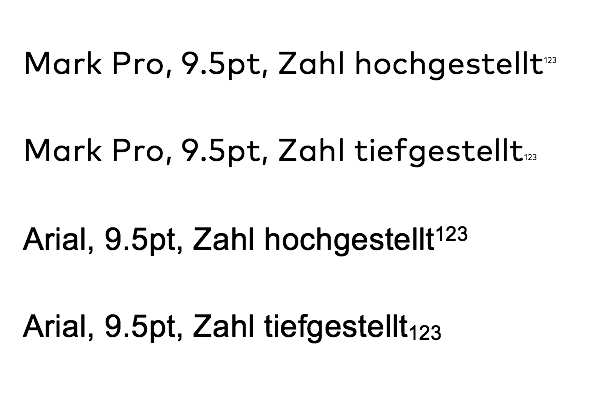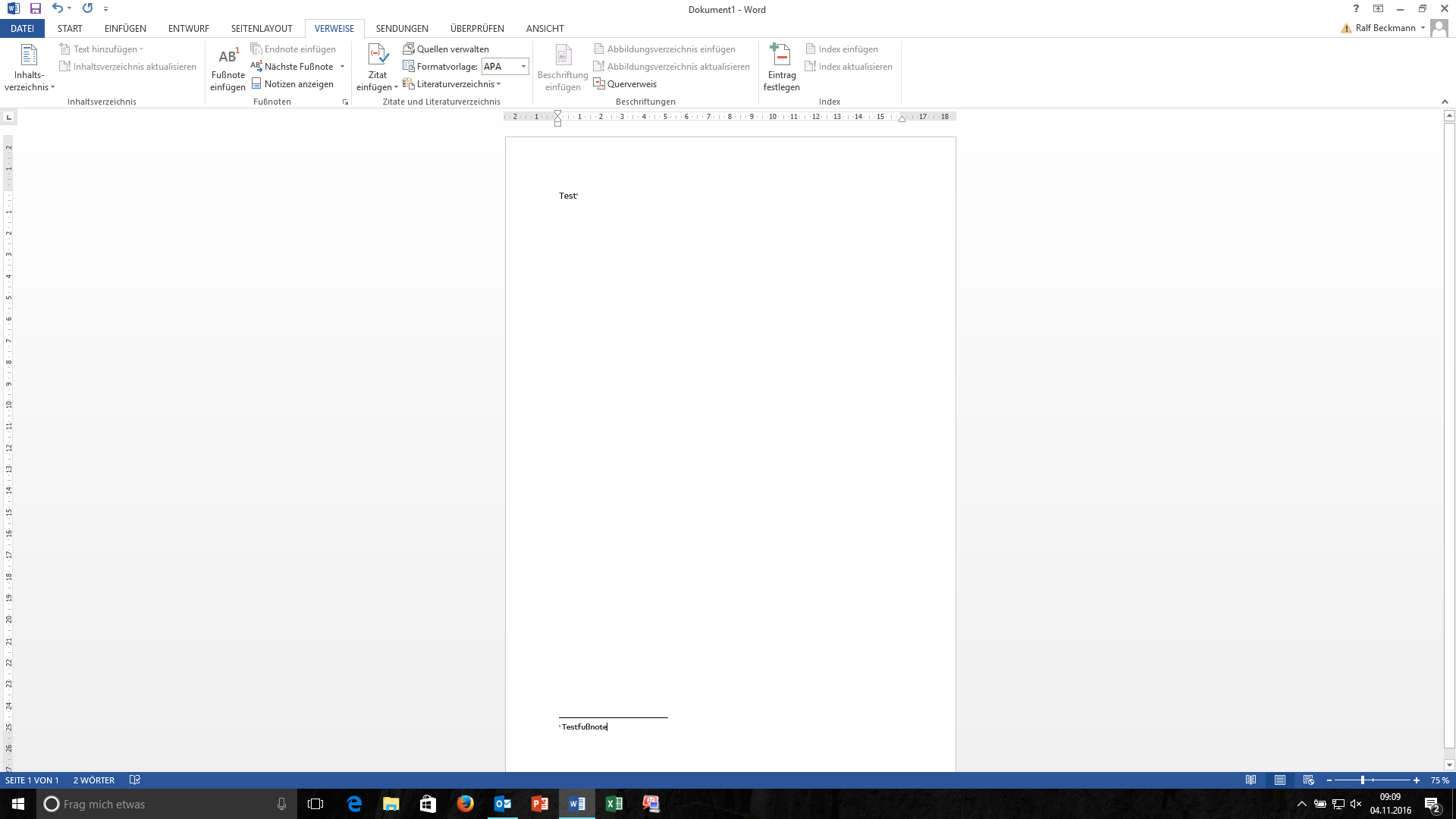
Word und FF Mark: Probleme mit Hoch-/Tiefstellen
folgendes Problem: Unser Kunde kommt mit der Schrift FF Mark (Open Type) in MS Word nicht zurecht. Hoch- oder tiefgestellte Zeichen werden viel zu klein dargestellt, siehe Screenshots. Die Option, die Schriftgröße manuell einzustellen, ist sehr umständlich und kein zufrieden stellender Weg, daher meine Frage, ob es hier bessere, konkrete Ideen zur Ursache sowie zur Lösung des Problems gibt.
Woher bekommt Word die Informationen für das Hoch-/Tiefstellen? Und lassen sich diese einstellen?
Tja, Word ist halt nix für anspruchsvolle Typografie. Prinzipiell gibt es zwei Wege, Texte mit hoch- und tiefgestellten Ziffern zu erzeugen. Der beste Weg ist es, spezielle Hoch- bzw. Tiefziffern aus modernen Fonts zu verwenden, die in Größe, Position und Strichstärke genau auf ihre Schrift abgestimmt sind.
Solche Fonts gibt es aber noch nicht so lange. Daher haben Programme wir Word diese Ziffern oft künstlich erzeugt, indem sie die normalen Ziffern verkleinerten und nach oben bzw. unten schoben. Durch das Verschieben ist die Position der Ziffern dann von Programm zu Programm verschieden und sieht mal besser und mal schlechter aus. Ein gravierenderes und praktisch unvermeidbares Problem dieser Methode ist, dass die verkleinerten Ziffern dann eine viel zu geringe Strichstärke haben. Das siehst du oben in beiden Beispielen.
Warum es aber in der Mark noch viel extremer passiert als in der Arial, hmm, da muss ich spekulieren. Vielleicht werden ja die schon angepassten Hoch- und Tiefziffern der Mark verwendet, aber fälschlicherweise noch zusätzlich verkleinert, als wenn sie normal große Ziffern wären?
Welche Word-Version wird denn verwendet? Die neuste? Die Unicode- und Opentypeunterstützung ist in den letzten Versionen besser geworden, auch wenn sie noch lange nicht als professionelle DTP-Software heran reicht.
Nun, Word trau ich nach meinen Experimenten nicht für 5 Cent in Sachen OpenType, wenns dann keine eigenen Microsoft-Schriften sind, und da hat sich bei meinen Experimenten herausgestellt, das hier Word die OpenType-Funktion intern nachbildet.
Daher schätze ich mal, das Word hier generell die Subscript und Superscript aus der normalen Schrift durch skalieren und verschieben macht.
Und da sind in der Schrift eben auch die Positions- und Skalierungswerte hinterlegt, in Fontlab bei Arial schaut das so aus, möglich dass  in der Mark da ungünstige Werte drin stehen, zumal ich da auch noch nicht so voll durchgestiegen bin, was genau diese Werte aussagen, besonders die Size-Werte.
Stimmt, dann wir es so sein, dass diese Skalierungswerte in der Mark ungünstig gesetzt sind - und den Profis ist es nicht aufgefallen, weil sie eben i.a.R. die im Font vorhandenen Hoch- und Tiefziffern ohne Skalierung nutzen.
Ein Bugreport an Schrifthersteller oder -verkäufer sollte helfen.
Gut möglich, das da schlicht die Vorgabe des Font-Editors so belassen wurde.
Lege ich einen neuen Font an, bekomme ich diese Werte:newfont.JPG
Wenn ich dann den vorgegebenen UPM-Wert  von der Vorgabe 1000 auf z.B. 2048 um stelle, den Font aber dabei nicht skaliere, weil ja eh noch keine Glyphen drin sind, bleiben die Vorgabewerte für Superscript und Subschript unverändert.
Und diese nahezu um die Hälfte zu kleinen Werte passen ziemlich genau zu dem, was da die Mark Pro liefert. Gut möglich, das da der Schriftgestalter überhaupt nicht hinein geschaut hat.
Über „Symbol einfügen“ geht es. Soweit ich mich erinnere, kann man die Zeichen aber auch unter Windows direkt über die Tastatur eingeben, ohne den Dialog für die Sonderzeichen aufzurufen. Dazu muss man, glaube ich, eine kleine Änderung am System vornehmen. Aber man kommt auch dann nicht darum herum, die Codes auswendig zu lernen, wenn es schnell gehen soll.
Unicode
1: 00b9
2: 00b2
3: 00b3
0 und 4–9: 2070 und 2074–2079